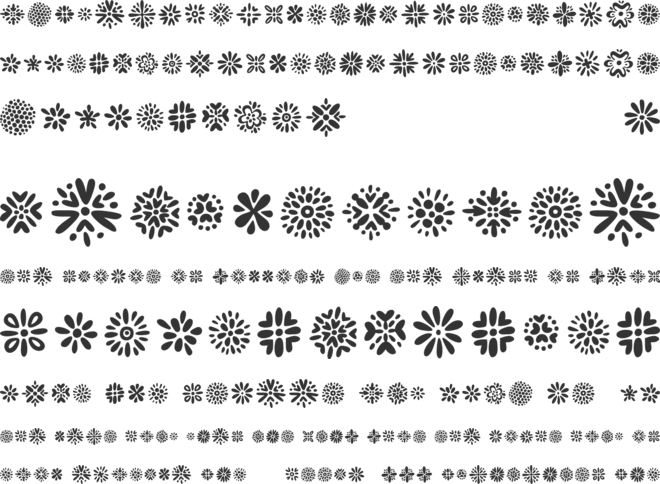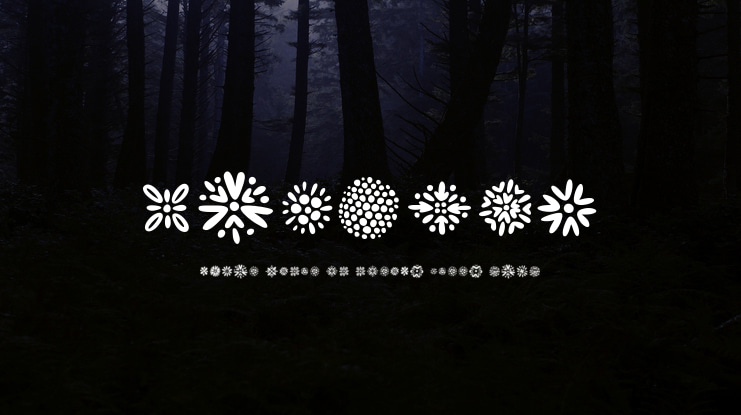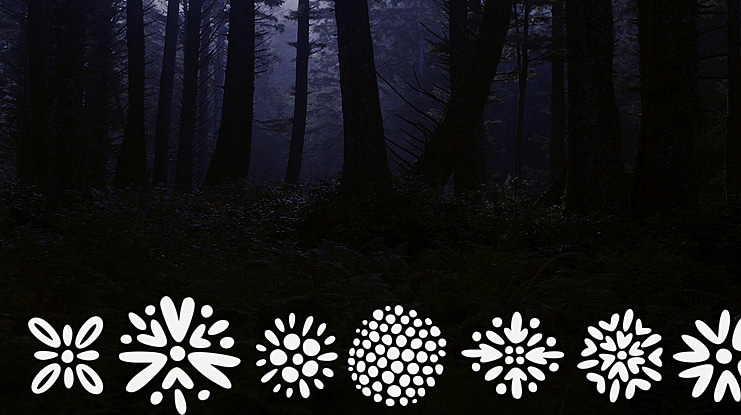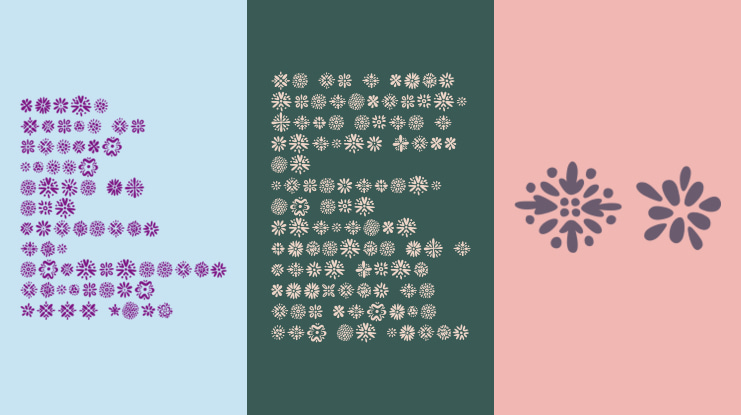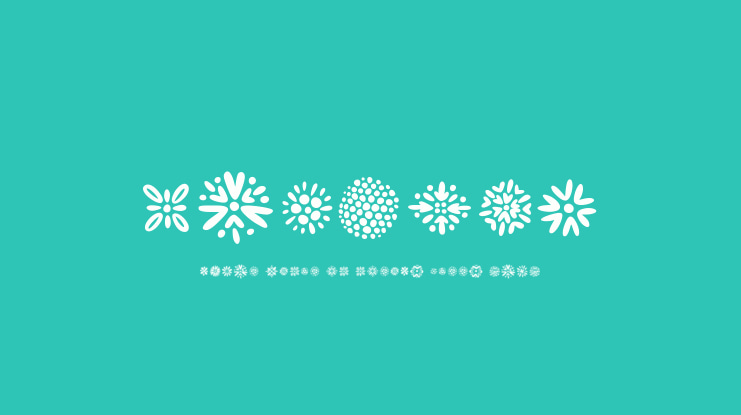
Kembang Font
Sewaktu menelpon seseorang, mengebrol panjang lebar, daripada tangan tidak berbuat apa-apa, maka saya menggambar bentuk-bentuk bunga ini. Semoga kamu suka ya! :) Ingat selalu untuk tersenyum :)